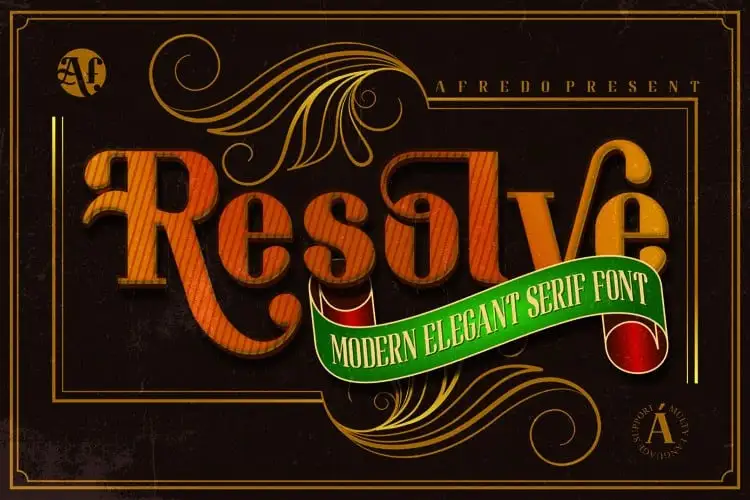
Resolve Serif Font – Download Grátis
Resolve Serif Font é uma elegante fonte serif que oferece um leque variado de ligaturas e alternativas. Ela é perfeita para aplicativos de marcação, cartões de visita, citações, postagem, logotipos e muito mais, impressionando com sua beleza. O designer afredo.fk criou este fonte meticulosamente e compartilhou-o no site 99designs. É uma escolha perfeita para quem busca um estilo sofisticado que se destaca em qualquer aplicação gráfica.